書体転生(30フォントSET)
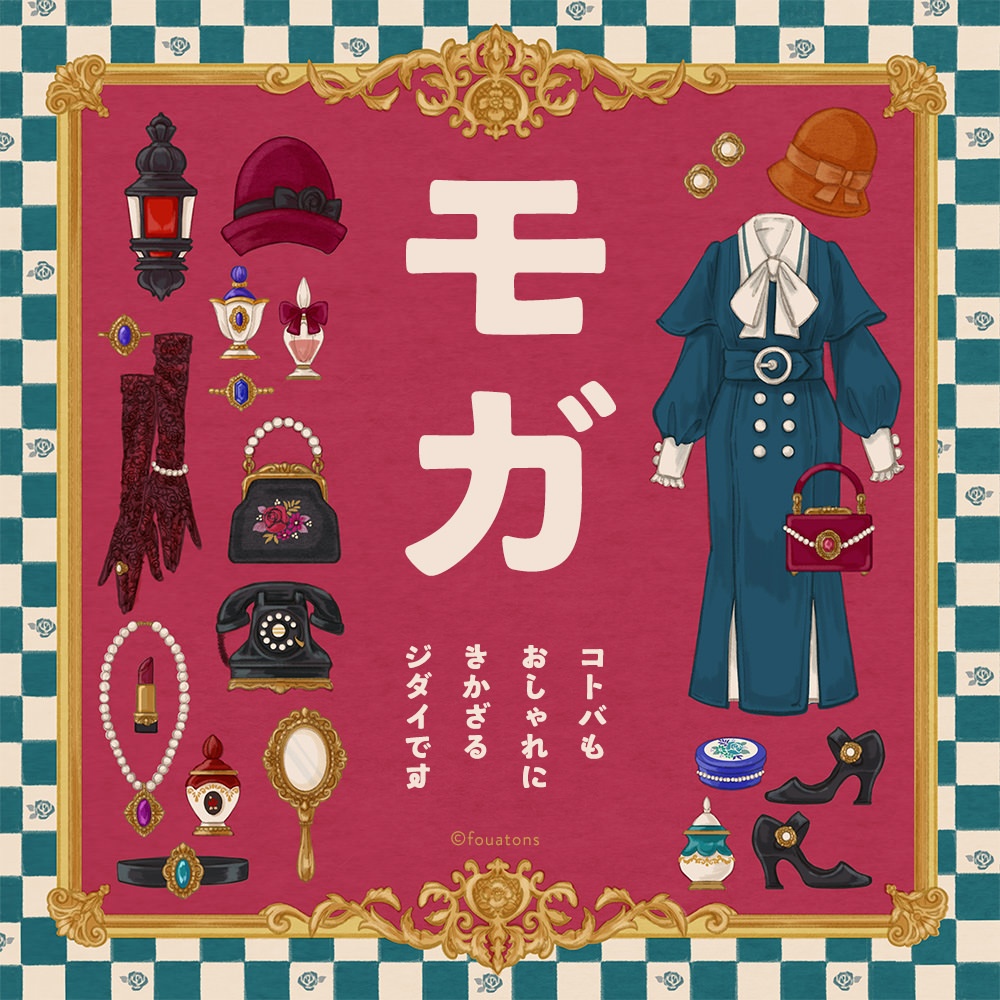
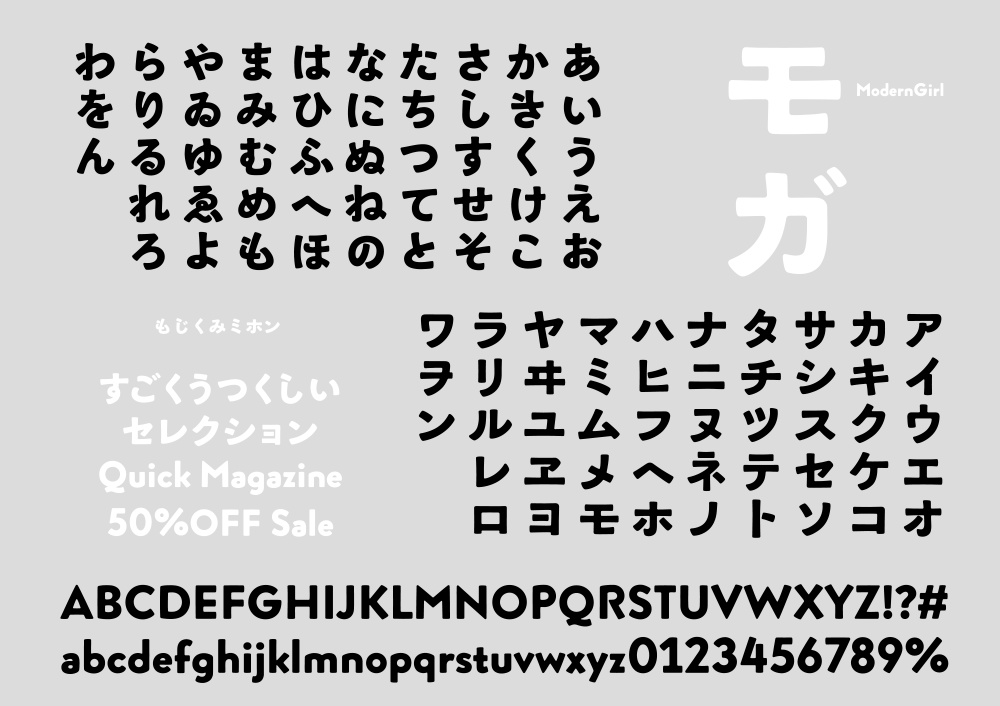
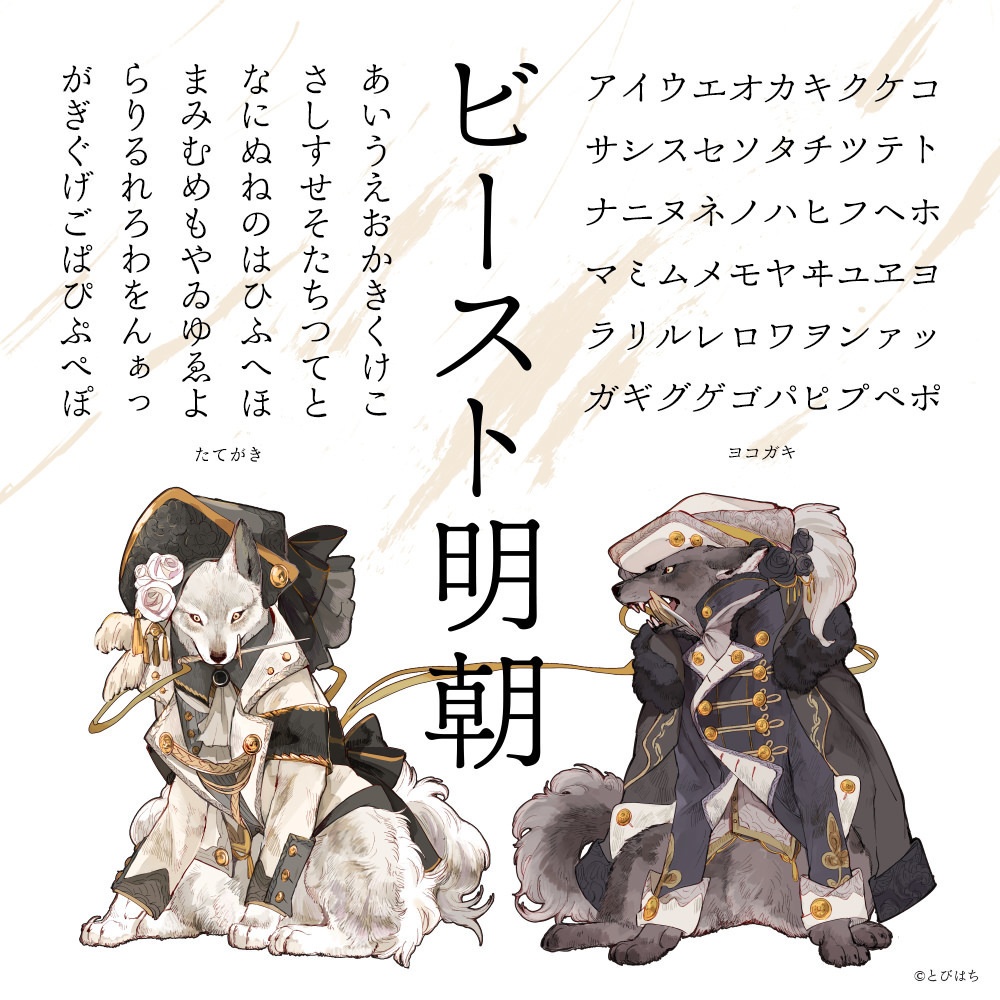
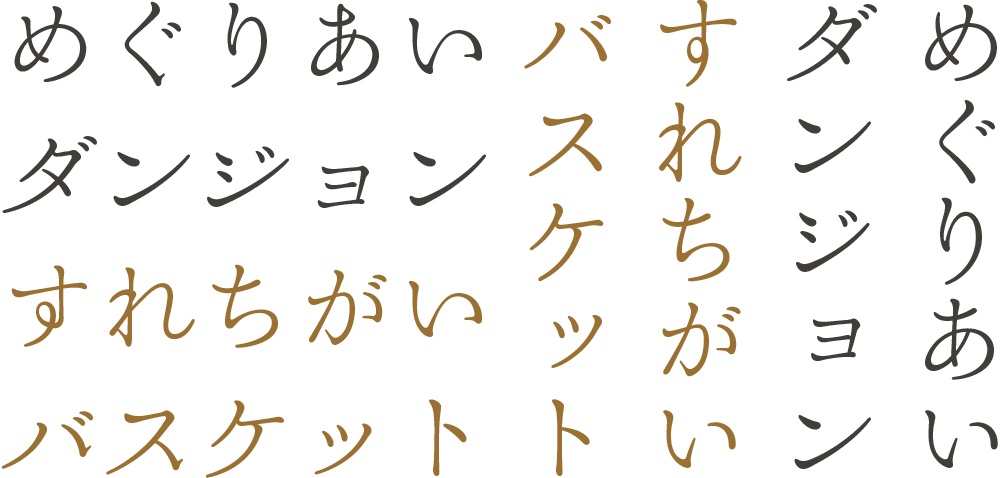
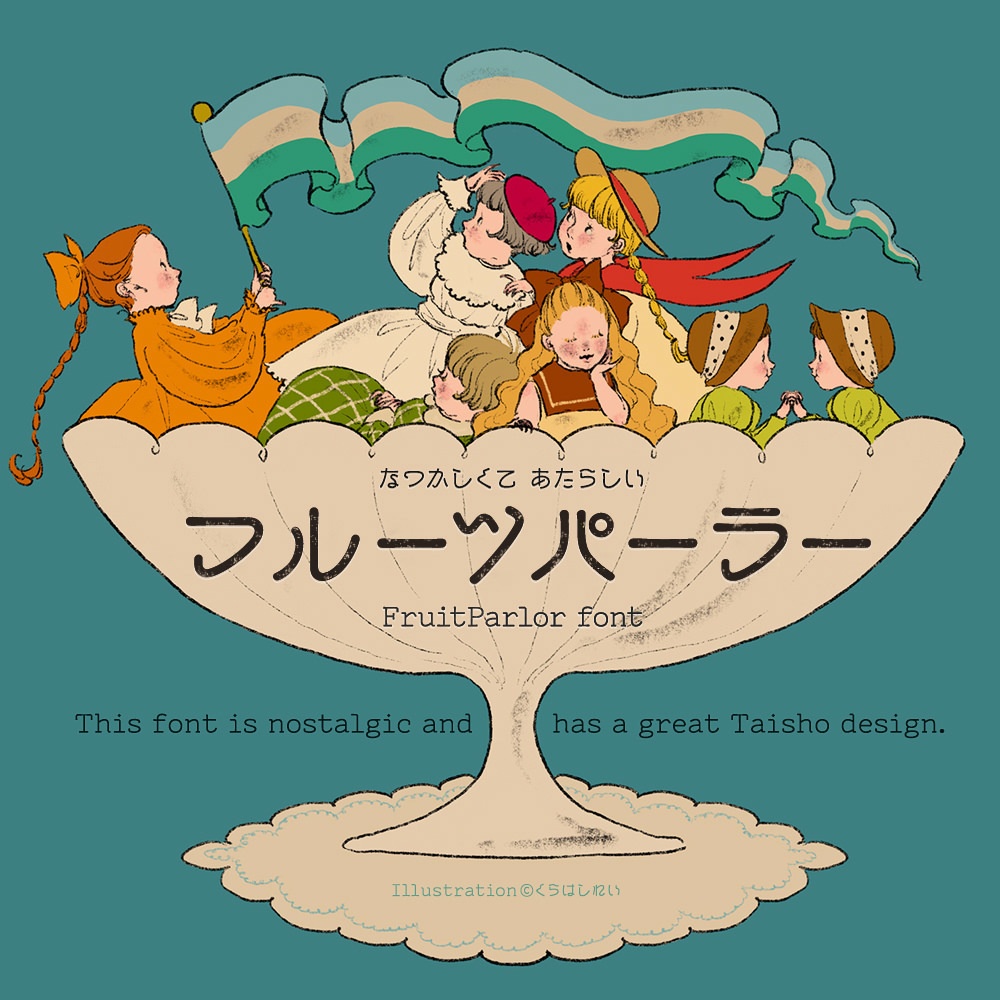
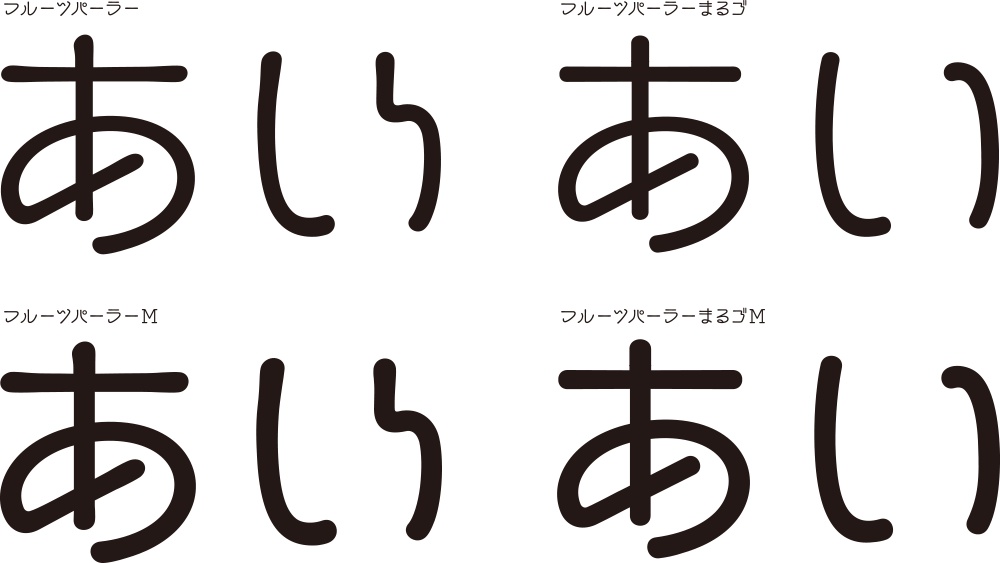
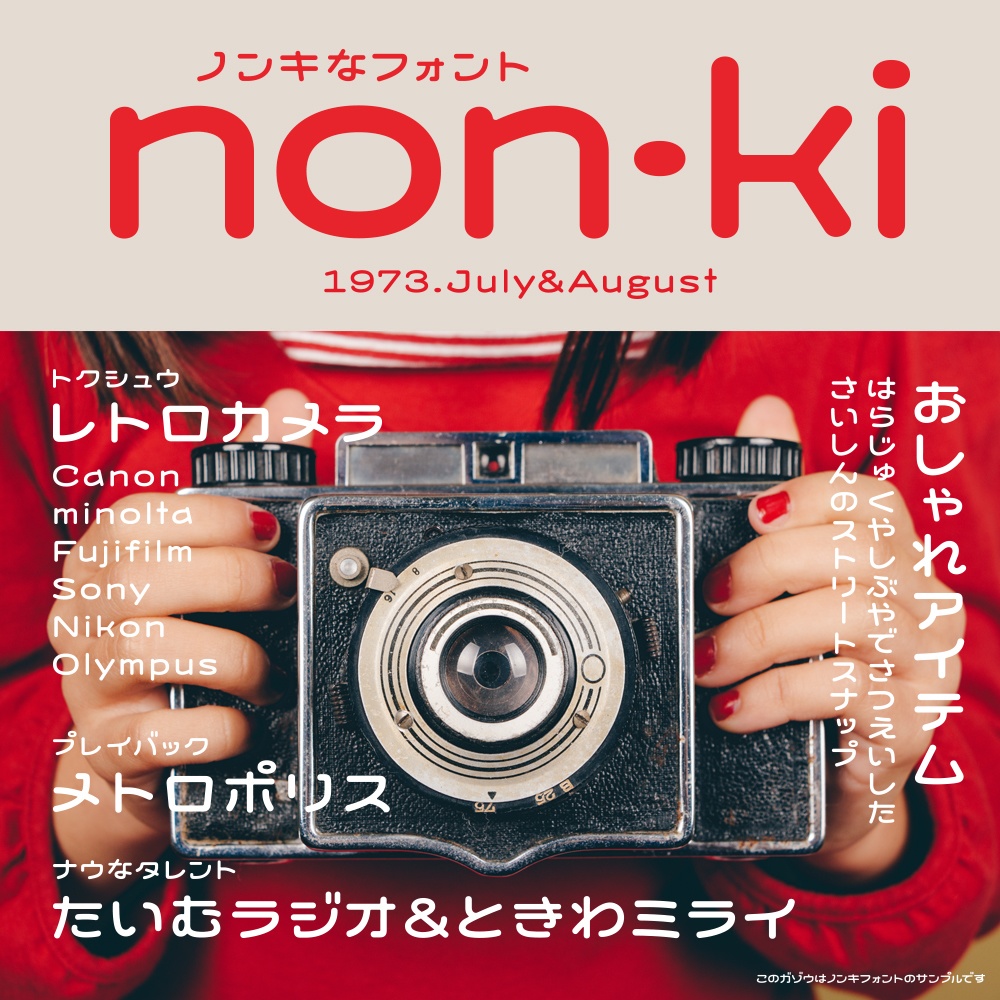
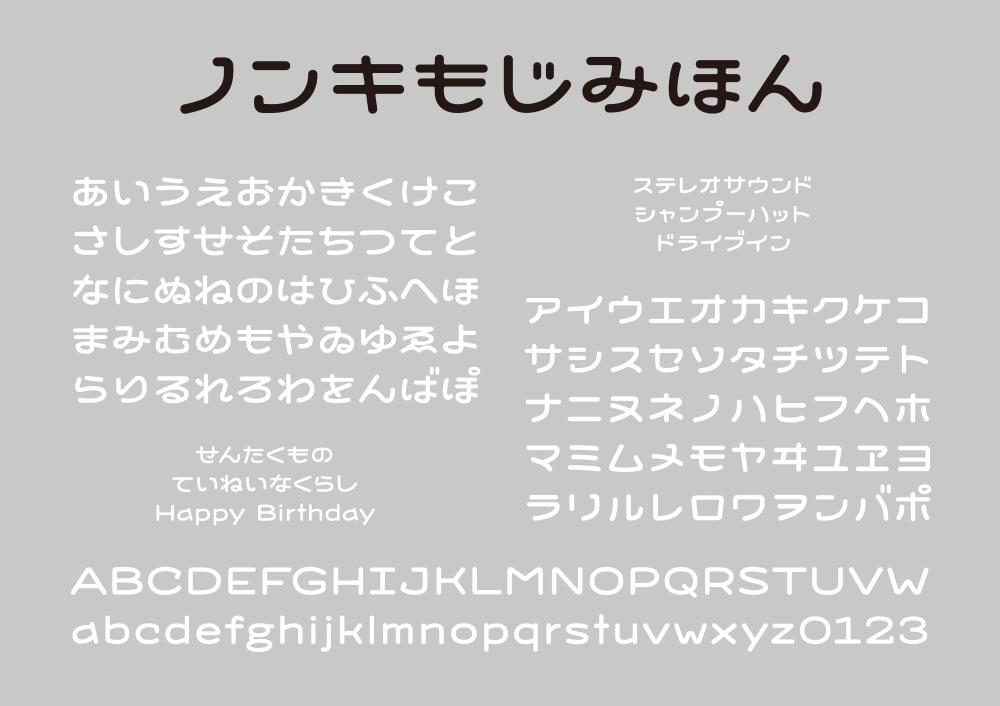
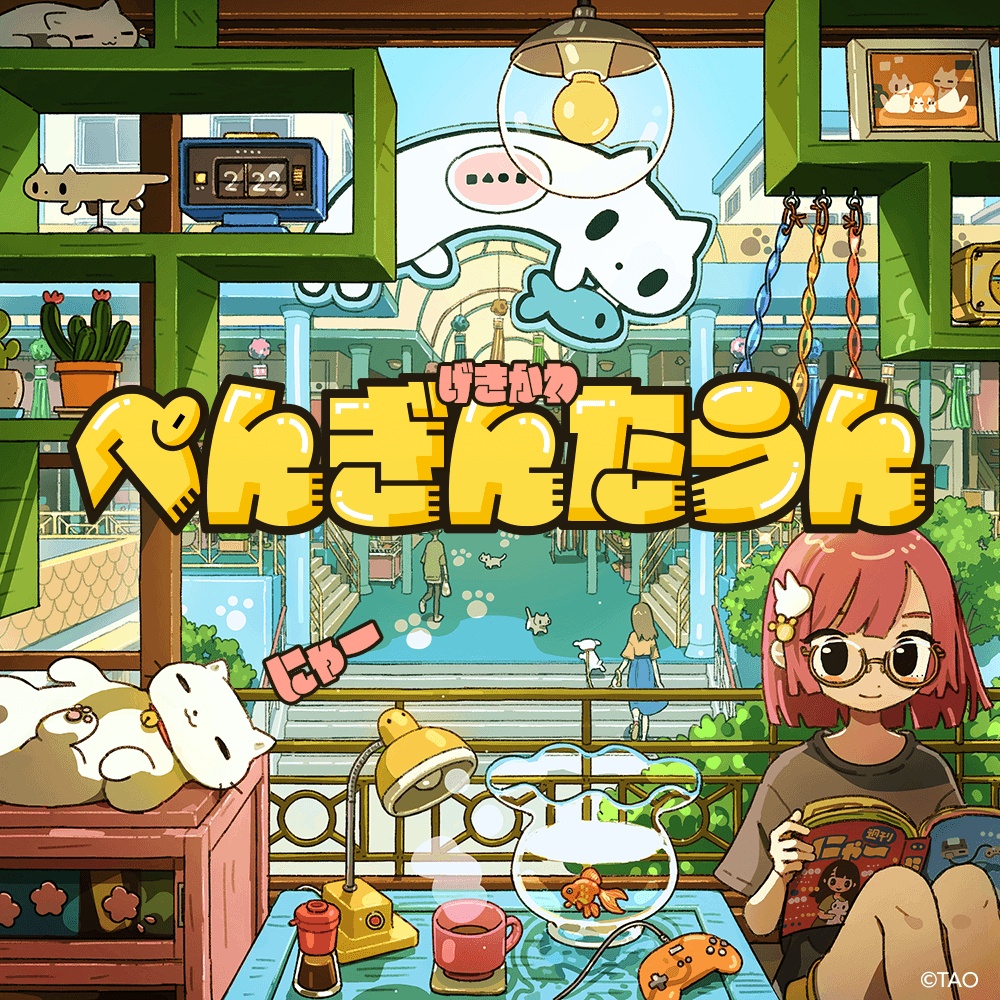
新しい視点で生み出されたハイセンスなフォント集。古い時代の文字を、まったく新しい書体に生まれ変わらせたフォントが多いのも特徴です。大正時代の活字からインスピレーションを得たモガ。縦書きと横書きで字形が異なるビースト明朝。極めてレトロな字幕書体フルーツパーラー。1970年代の雰囲気のノンキ。80年代風の超極太POP体のぺんぎんたうん。シンプルな角ゴシックのヨハク。手描き風の、かなたとひなた。自由なラインのうたとキャロル。超可愛いくてポップなとらいあんぐる。他のフォントと組み合わせることで、魅力が倍増するフォント達です。 収録フォント モガ、ビースト明朝、フルーツパーラー、フルーツパーラーまるゴ、フルーツパーラーM、フルーツパーラーまるゴM、ノンキ、ぺんぎんたうん、ぺんぎんにゅーたうん、ぺんぎんたうんポップ、ヨハク(9フォントset)、かなたとひなた(8フォントset)、とらいあんぐる(2フォント)、うたとキャロル 動作環境 Mac:システム/OS X対応(10.x)最新のOS X Windows:OS/日本語版Windows2000、XP、VISTA、Windows7〜11以降 フォント形式:OpenTypeフォント、TrueTypeフォント ※Adobeイラストレーター、フォトショップはもちろんのことWindows用ワード・エクセル等でもご使用になれます。 1商品(1ライセンス)につき1ユーザー1PCのみがご利用いただけます。